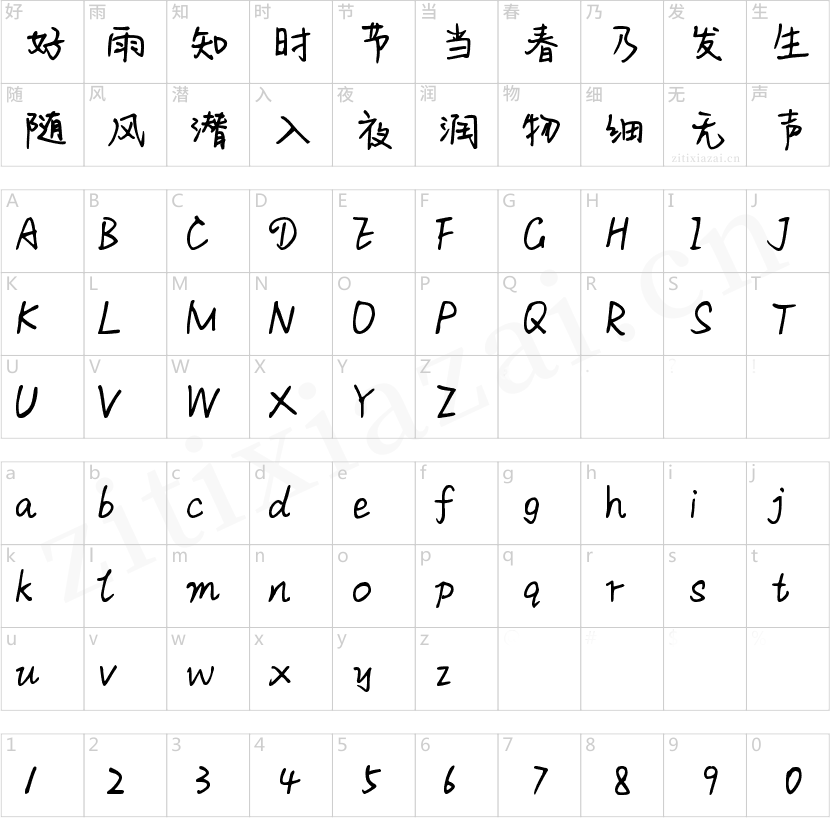
Aa夕禾
Aa夕禾,这款字体结构工整、笔画清晰,兼顾美观与易读性,适用于标题、正文、海报、包装、LOGO 等多种场景。字形优雅稳定,风格百搭耐看,适配日常排版与创意设计,让文字呈现更舒适、更具质感。Aa夕禾一笔一画,皆是细节,以均衡的比例、流畅的线条打造舒适视觉体验,字形端正大气,风格简约现代。无论是商业设计、品牌宣传还是日常排版,都能轻松驾驭,让文字更有格调与力量。Aa夕禾字体下载。
Aa夕禾是一款非常具有艺术性的字体,它的设计灵感来源于对古典艺术的研究,同时又融入了现代字体设计的元素。字形优美,笔画粗细变化自然,给人以大气、典雅的感觉。Aa夕禾是一款既传统又现代的字体,它的设计充满艺术感,美观大方,实用性也非常强。无论是对于设计师还是对于普通读者来说,都是一种非常不错的字体选择。Aa夕禾适合用于具有艺术感的场合,比如海报、宣传单张、书籍封面等。由于其字形流畅且具有动态感,也适合用于大量的文本排版,如报纸、杂志等。